要了解汉字的设计,首先应对各种书写体作系统的了解,这样才能融汇贯通,灵活应用。中国的书体,通常所说的有“正草隶篆”四体,但由于工具特殊,各代书家作书运笔神妙,出现许多不同的变化字体,成为多种特殊的艺术造型。
中国字体从纯粹的绘画演变为线条符号而言,大致可分为下列六体:
古文
上古时代的象形文字,包括商朝的甲骨文字体和三代的金文两种。
草书
有组织系统的简省字体。创自汉初,其演变过程是先有“章草而后有“今草”至后又有“狂草”。一般草书在造型上难为大众了解,又缺乏实用与易读性,不适用于一般文字设计用。不过用于感谢等需要表达亲切印象时,因草书具有个性,即信赖、亲切、高雅等特性用之得法也不失为好素材。
行书
是正书的变体。中国文字,自唐以后,即少变化;而行书就被认为最流行的字体,一直沿用到现在,在实用美术上仍保有崇高的地位。行书易识好写,实用范围广。目前社会上除了印刷及重要文字得用正书字外,日用文书一般都用行书书写。
现代汉字设计,基本都是按以上六种和印刷体中的老宋、仿宋、黑体等体例,进行演变加工得来的,重点要掌握每个字的基本笔划及有规律性的组织变化,考虑笔划间的空隙均衡使设计的商标;广告、标题、或包装装演,既得体又美观大方。设计形象性和装饰性的美术字,变化要自然适度,切忌过分夸张。因为过分的夸张,会显得矫揉造作,其效果会走向反面。
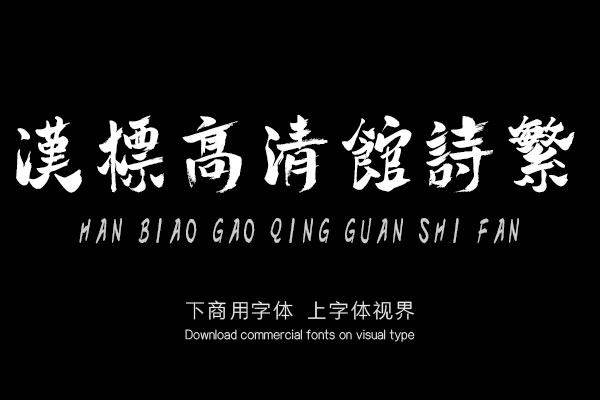
正书
又称“楷书”,揉和隶书、草书而成的一种书体,至今已成为一般书籍信件最通行的标准字。现在印刷活字的“正草”就是传统的“正书体”,它的笔迹有力,字划清楚,易读性最高。
篆书
有西周后期的大篆和秦时的小篆二体。篆书,具有古代象形文字的古朴感,其图形的抽象趣味在近代的篆刻上常被艺术化了。在现代的应用美术中,尤其是国内设计界多把篆书应用于贺年卡、请帖、徽章图案等设计。
隶书
源于秦代,取大篆与小篆的笔法,加以减省整理而成。隶书不仅变秦以前字体的曲线为直线,变划为点,变圆为方,且渐脱离形进于意符,隶书的特点是:一、每个字有一处(横划与右捺)带有波势的装饰笔。二、横划以右斜落笔书写。在广告设计里,凡公司。行号或展示会的全名设计(合成文字)常用隶书,可表现传统的权威感。